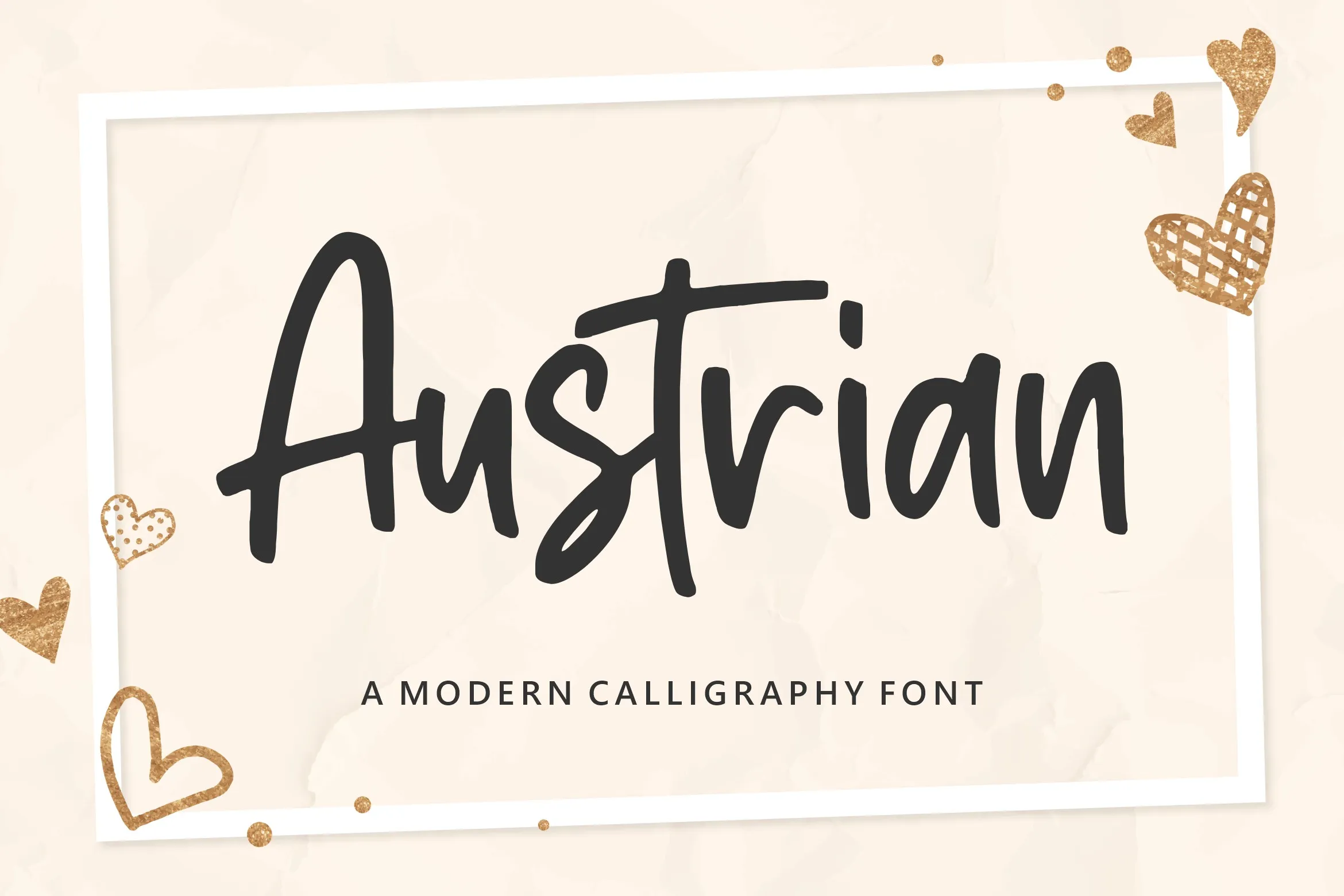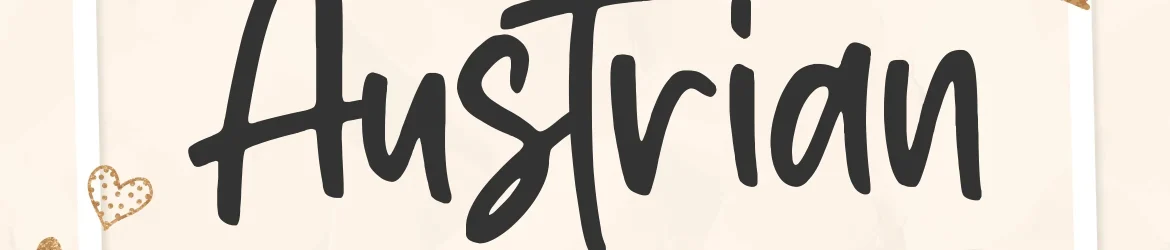
Austrian Font – Download Grátis
A Austrian Font é uma elegante e delicada fonte escrita a mão que traz um toque romanticamente suave e alegre. Ideal para aqueles projetos personalizados, como cartas de casamento ou qualquer outra necessidade de design requintado e pessoal, esta fonte é perfeita para dar um toque romântico ao seu trabalho. Seja em eventos festivos ou em designs que exigem uma atmosfera delicada e acolhedora, a Austrian Font estará sempre pronta para complementar suas criações de design, oferecendo um toque inconfundível de elegância e romantismo. Com sua versatilidade, essa fonte será o recurso gráfico perfeito para designers em busca de uma sensação delicada e única no seu trabalho.